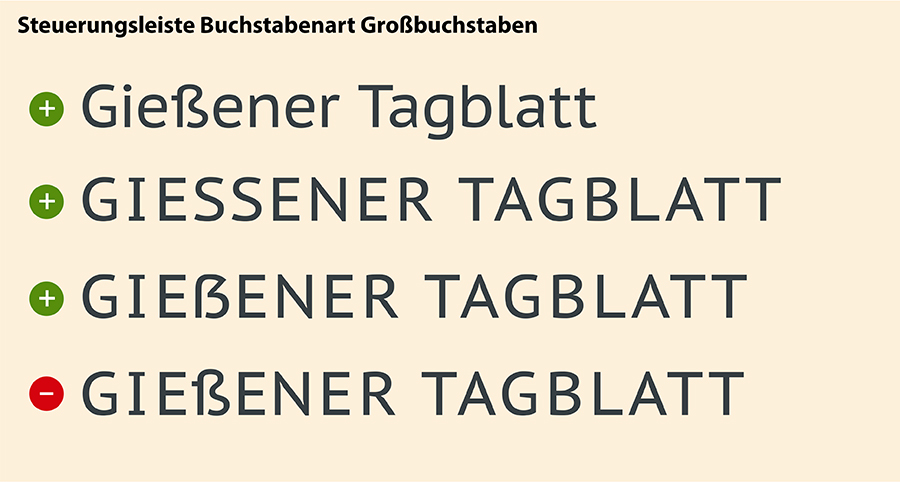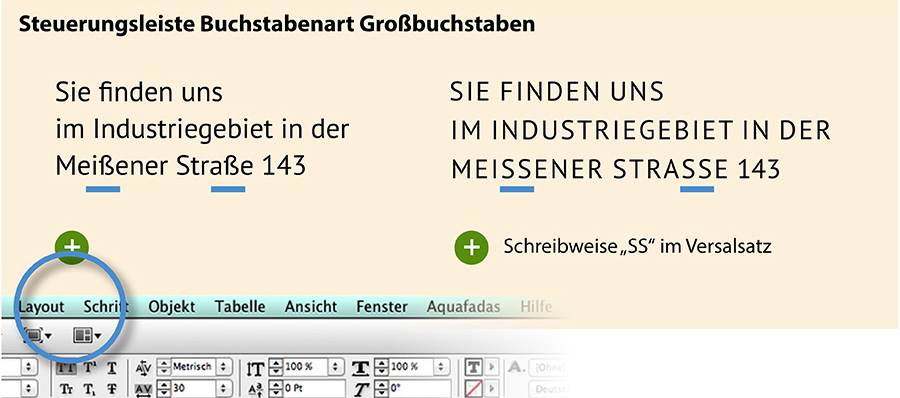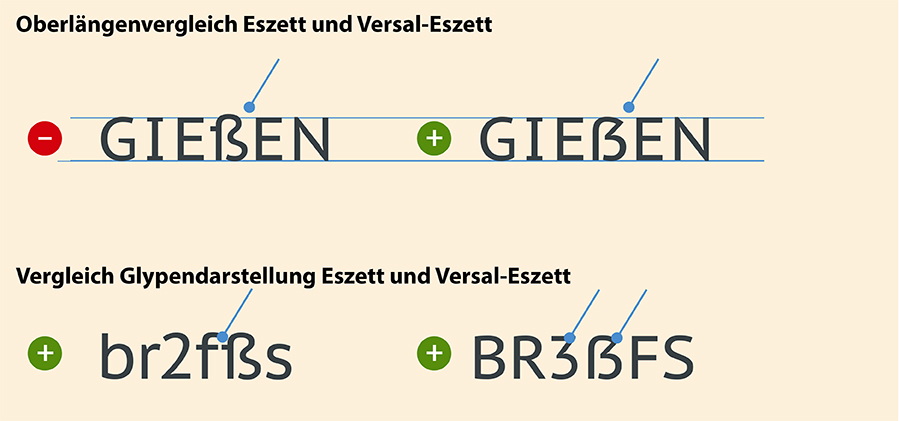
So geht’s richtig: Eszett, Doppel-s und Versal-Eszett in Typografie und Rechtschreibung
ß, SS und Versal-Eszett in der Typografie
Wenn man dem Einwohnermeldeamt meines Heimatwohnsitzes glauben darf, dann wohne ich in der „PARKSTRAßE.“ Darüber ärgere ich mich jedes Mal, denn oft erscheint das „ß “ – vor allem im Behördendeutsch – im Versalsatz wie ein „B“. Besser wäre es, man würde in der Schweiz wohnen, denn in der schweizerischen Rechtschreibung gibt’s das „ß“ gar nicht. In Deutschland (und in Österreich) müssen wir uns typografisch jedoch damit auseinandersetzen. Deshalb im Folgenden ein paar Tipps, Hinweise und Empfehlungen rund ums „ß“.
Seit 2017 ist das Versal-Eszett in der deutschen Rechtschreibung gültig
Den Wunsch nach einem Großbuchstaben für das „ß“ äußerte der Duden bereits in einer Rechtschreibempfehlung im Jahre 1925. Aus dem Wort „Straße“ sollte im Versalsatz „STRASZE“ werden. Seit 2017 ist in der deutschen Rechtschreibung im Versalsatz zwar die Schreibweise des Versal-Eszett nun endlich gültig, jedoch schreibt man das kleine „ß“ auch als „SS“.
Adobe InDesign kann’s richtig
Im oberen Bildbeispiel wurde das Eszett als Kleinbuchstabe für den Versalsatz verwendet und nicht gewandelt. Wenn Sie einen Text in InDesign setzen, diesen aktivieren und mittels Steuerungsleiste in Großbuchstaben umwandeln, ersetzt Adobe InDesign das „ß“ automatisch durch die korrekte Schreibweise „SS“. Wenn der Font nicht über die Glyphe Eszett verfügt oder Sie aus ästhetischen Gründen kein Eszett im Versalsatz anwenden wollen, sind Sie mit dieser Methode auf der sicheren Seite.
Automatische Umwandlung von ß in SS
Das Versal-Eszett als Alternative zur Schreibweise versales Doppel-s
In der Tat verfügen manche Satzschriften über ein Versal-Eszett als Glyphe, das als alternative Schreibweise von versalem Doppel-s verwendet werden darf. Dabei gibt es für das Versal-Eszett keine feste Tastaturbelegung, sondern Sie finden das Zeichen in InDesign unter: Menü / Schrift / Glyphe / Einblenden: Alternativen für Auswahl. Inwieweit das Versal-Eszett jedoch gestalterischen Sinn macht und ob es sich typografisch harmonisch in den Titelsatz integriert, das sollten Sie als Designer selbst entscheiden. Hier einige Beispiele mit der PT Sans Caption aus der Fontschmiede ParaType aus Kalifornien:
Richtung und falsch: Einsatz von ß, SS und Versal-Eszett in Schriften
Worin unterscheiden sich typografisch Eszett und Versal-Eszett?
Am deutlichsten unterscheidet sich das Versal-Eszett vom Eszett in der Typometrie an der Oberlänge. Das Versal-Eszett hat als Großbuchstabe die gleiche Höhe wie andere Großbuchstaben. Das normale „ß“ hingegen ist ein Kleinbuchstabe und weist somit die gleiche Oberlänge wie „b“, „d“ oder „l“ auf. Auch gestaltet sich das Versal-Eszett meist viel eckiger und passt sich gestalterisch mehr den restlichen Großbuchstaben an (oder versucht es meistens zumindest). Hier ein direkter Vergleich:
Oberlängenvergleich zwischen Eszett und Versal-Eszett
Fazit: „ß“ und Versal-Eszett in Rechtschreibung und Typografie
• Laut Duden wird „ß“ seit der Rechtschreibreform von 1996 im Versalsatz als versales Doppel-s geschrieben.
• Das Versal-Eszett ist in der deutschen Rechtschreibung seit 2017 verankert.
• Das Versal-Eszett ist aber als alternative Schreibweise zu Doppel-s im Versalsatz möglich.
• Es gibt keine einheitliche Tastaturbelegung für ein Versal-Eszett.
• Wenn Sie ein Versal-Eszett verwenden möchten, achten Sie darauf, dass es sich um ein echtes, eigens entworfenes Zeichen handelt. Machen Sie den Oberlängen-Verglich!
• Sollten Sie eine Publikation für den Schweizer Sprachraum anlegen, muss das „ß“ generell durch die Schreibweise Doppel-s ersetzt werden – auch nach einem langen Vokal wie zum Beispiel in dem Wort „Strasse“.
Meine Empfehlung
Das Versal-Eszett ist als Zeichen in vielen Fonts weiter auf dem Vormarsch und seit 2017 in der deutschen Rechtschreibung gültig. Ich finde diese Alternative zum versalen Doppel-s brauchbar, wenn es den Schriftdesignern gelungen ist, aus dem eigentlichen Kleinbuchstaben einen Versalbuchstaben zu entwickeln, der sich in den restlichen Versalsatz optisch integrieren lässt. Ich verwende ein Versal-Eszett eher bei Titeln oder Markenlogos. Grundsätzlich sollten Sie Titelsatz und Absatztext nicht mit SS und dem Eszett mischen, sondern sich für eine einheitliche Variante entscheiden.